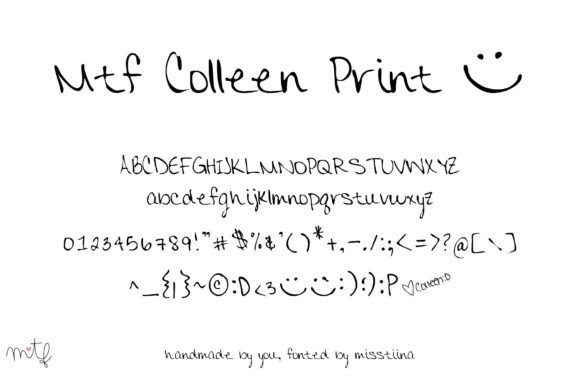
Colleen Print
適切なデザイン要素を見つけるのは難しい場合がありますが、Colleen Printは作品を即座に引き立てる優れたコレクションを提供します。
POD(オンデマンド印刷)製品、結婚式の招待状、またはソーシャルメディアのグラフィックを作成している場合でも、Colleen Printは理想的です。